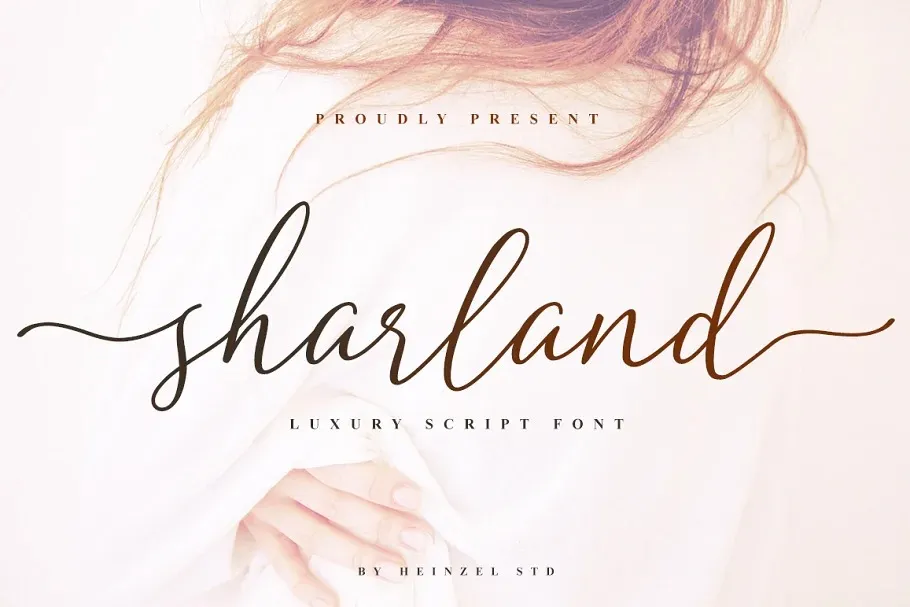
A Sharland Font é uma elegante fonte script que traz uma sensação moderna e sofisticada. Suas linhas finas e delicadas criam um charme único, tornando-a perfeita para usar em diversos projetos, desde identidades visuais até posts de redes sociais. Este script-font foi projetado para capturar a atenção de qualquer visualizador com seu design impecável. A fonte é PUA (Unicode Private Use Area) codificada, o que significa que você pode facilmente acessar todos os seus amados signos e ligaturas. Sharland oferece um toque moderno ao mesmo tempo em que mantém uma elegância clássica, tornando-a perfeita para criar design de casamento, cartões de aniversário, impressões digitais ou qualquer outro tipo de projeto. É sua vez de cair apaixonado por esta fonte e subir o nível dos seus trabalhos!